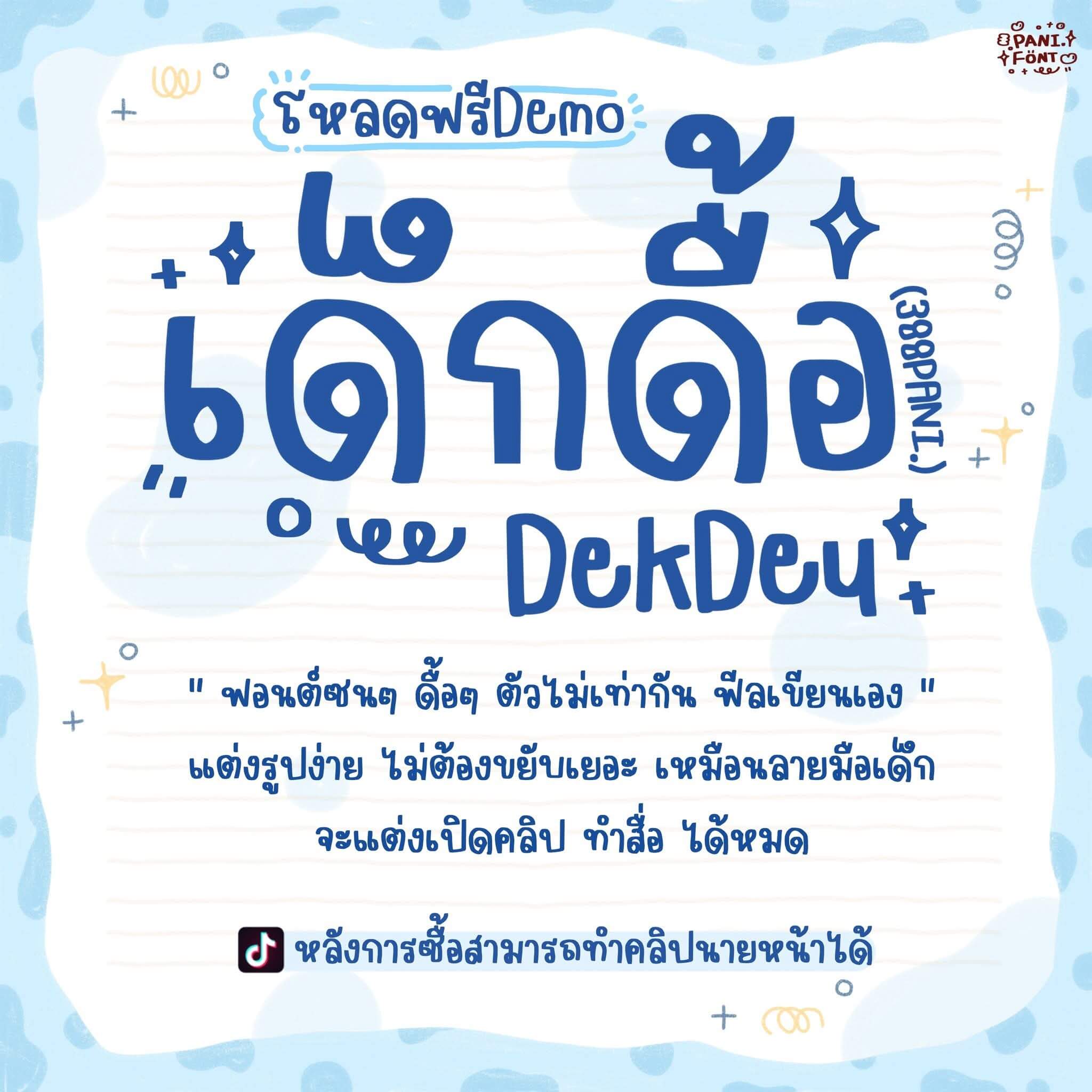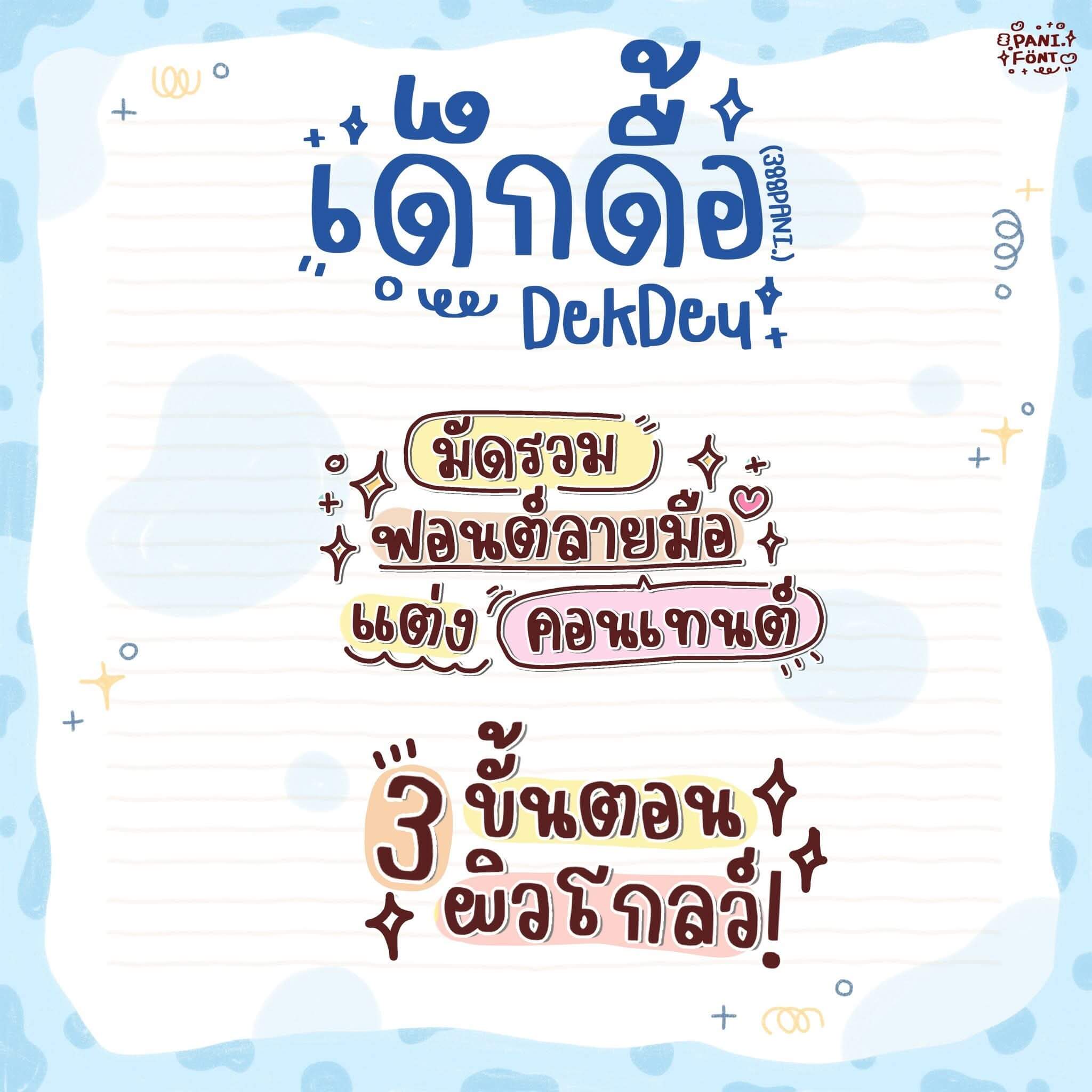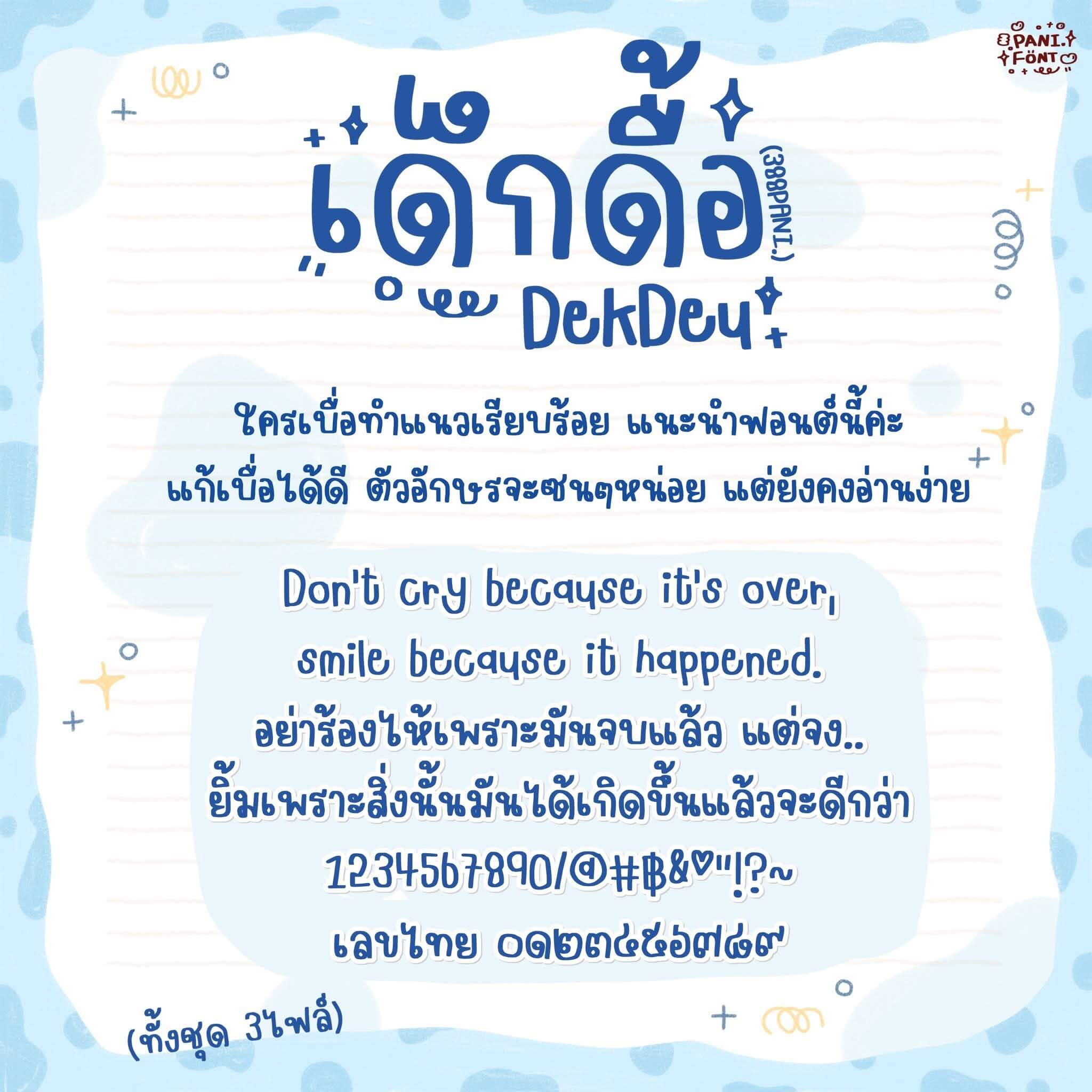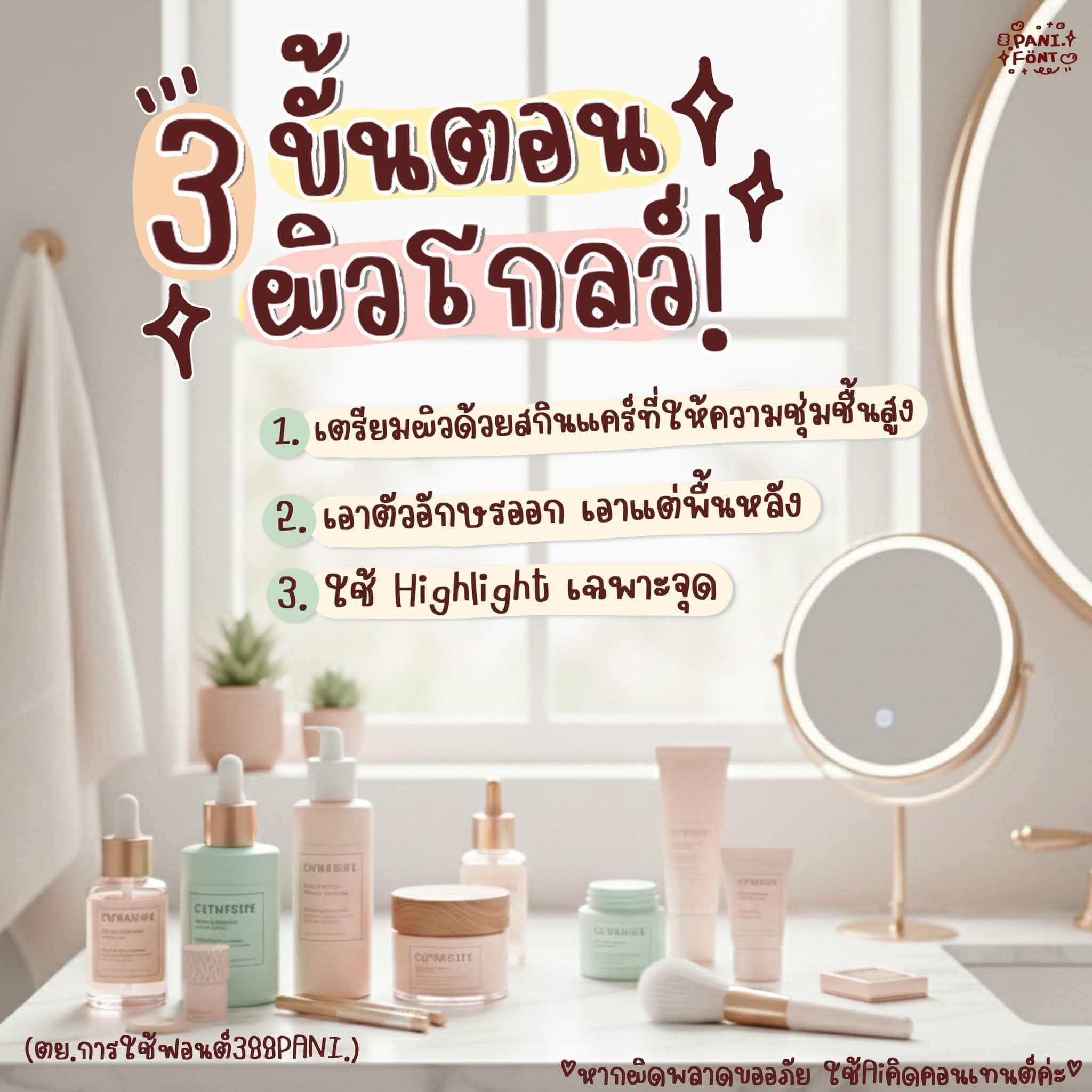
388PANI.เด็กดื้อ
ฟอนต์ 388PANI.เด็กดื้อ – ฟอนต์แนวซนๆ มัดใจใครได้มั้งมั้ยคะ สายคอนเทนต์ ทำคลิป ห้ามพลาดเลยค่ะ!! แต่งง่ายมากๆ ใครถนัดใน Phonto Cupcut ได้หมด